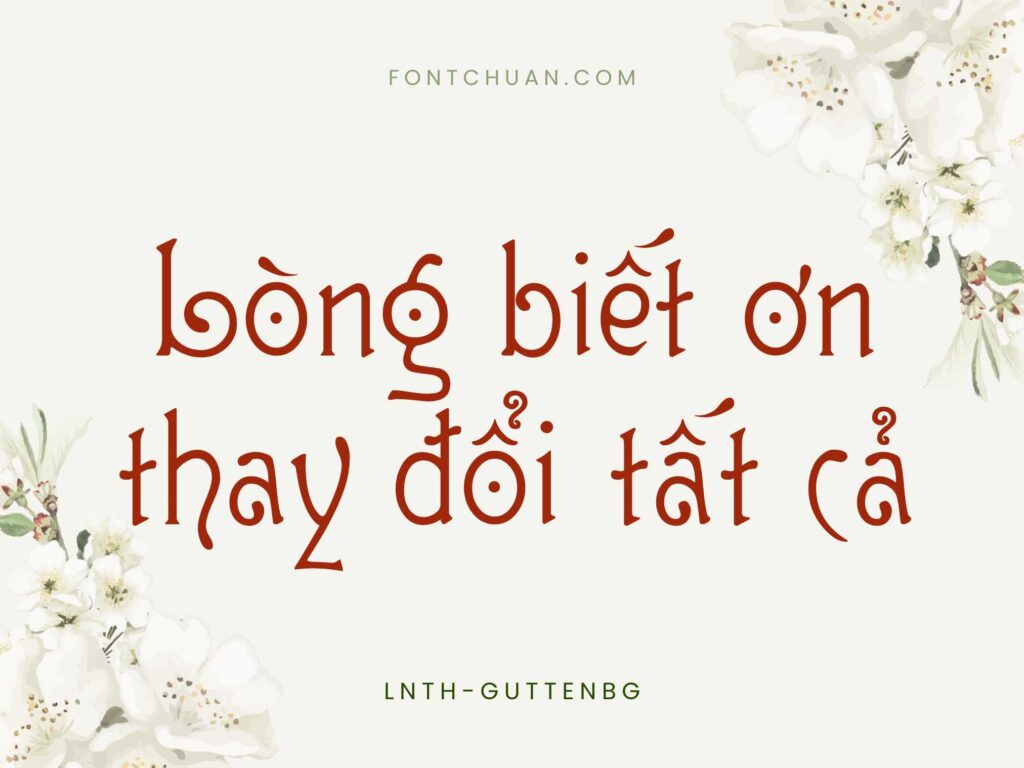
Font LNTH Guttenberg Mf Việt Hóa
Guttenberg MF là một phông chữ mang phong cách cổ điển, lấy cảm hứng từ kiểu chữ Gothic truyền thống thường thấy trong các bản in cổ và tài liệu lịch sử. Phông chữ này mang lại sự trang trọng và hoài cổ, phù hợp cho các thiết kế mang tính chất lịch sử hoặc cần tạo điểm nhấn mạnh mẽ. Phiên bản Việt hóa của LNTH giúp Guttenberg MF hỗ trợ đầy đủ các ký tự tiếng Việt, giúp người dùng dễ dàng áp dụng trong các dự án đa ngôn ngữ. Phông chữ này đã được sưu tầm và đăng tải bởi thành viên của Font Chuẩn nhằm đáp ứng nhu cầu đa dạng của cộng đồng thiết kế.
Về đặc điểm thiết kế, Guttenberg MF sở hữu các ký tự có đường nét sắc sảo, với những nét cong và góc cạnh đậm chất cổ điển. Phông chữ này đặc biệt phù hợp cho các dự án như thiết kế bìa sách, poster, logo, tiêu đề và các ấn phẩm quảng cáo cần sự trang trọng và ấn tượng. Ngoài ra, Guttenberg MF cũng thường được sử dụng như một Font chữ Trung Thu hoặc như một Font chữ Halloween, giúp tạo không khí huyền bí, cổ kính và ấm áp cho các thiết kế lễ hội. Font này cũng rất phù hợp cho các sự kiện như Halloween, lễ hội văn hóa và các dịp kỷ niệm truyền thống. Trong lĩnh vực ngành nghề, phông chữ này được ứng dụng rộng rãi trong quảng cáo, thiết kế thiệp cưới, giáo dục và công nghệ, góp phần tạo nên phong cách riêng biệt và thu hút cho các sản phẩm và thương hiệu.
Tác giả: Harry Dinh
Việt hóa: Harry Dinh